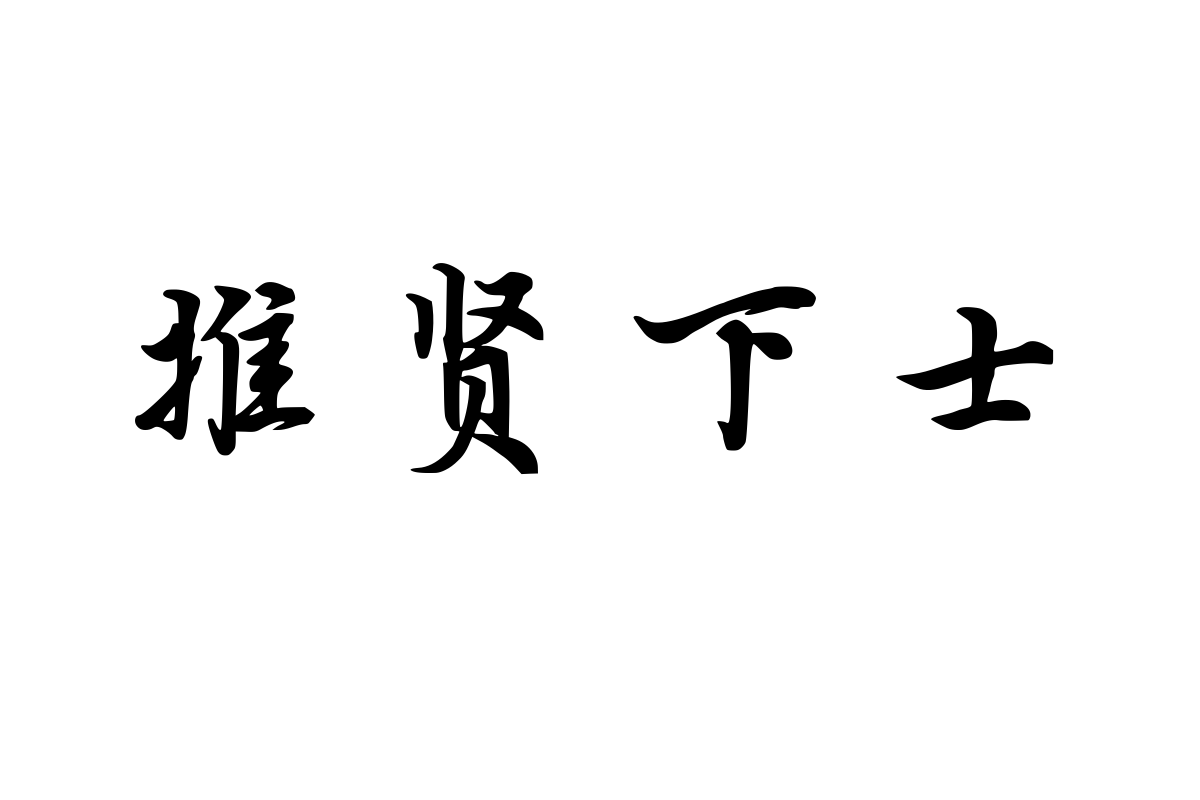
兰米如烟轻舞是一款具有艺术感的中文字体,它采用了独特的设计手法,将汉字的笔画和结构巧妙地融合在一起,形成了一种既简洁又富有美感的视觉效果。这款字体适用于各种需要强调文字艺术性的场合,如广告、设计、出版等。
兰米如烟轻舞的特点在于其轻盈飘逸的感觉,仿佛烟雾缭绕在空气中,给人一种梦幻般的感觉。同时,这款字体的笔画粗细适中,既有力度又有柔美,使得整个字体既有力量感又不失优雅。
兰米如烟轻舞的设计灵感来源于中国传统的水墨画,通过将汉字的笔画与水墨画中的线条相结合,创造出了一种独特的艺术效果。这种设计不仅使得字体更加独特,也使得它在视觉上更具吸引力。
总的来说,兰米如烟轻舞是一款非常出色的中文字体,它的艺术性和独特性使其成为了许多设计师和艺术家的首选。无论是用于书籍、杂志还是网页设计,兰米如烟轻舞都能展现出其独特的魅力。